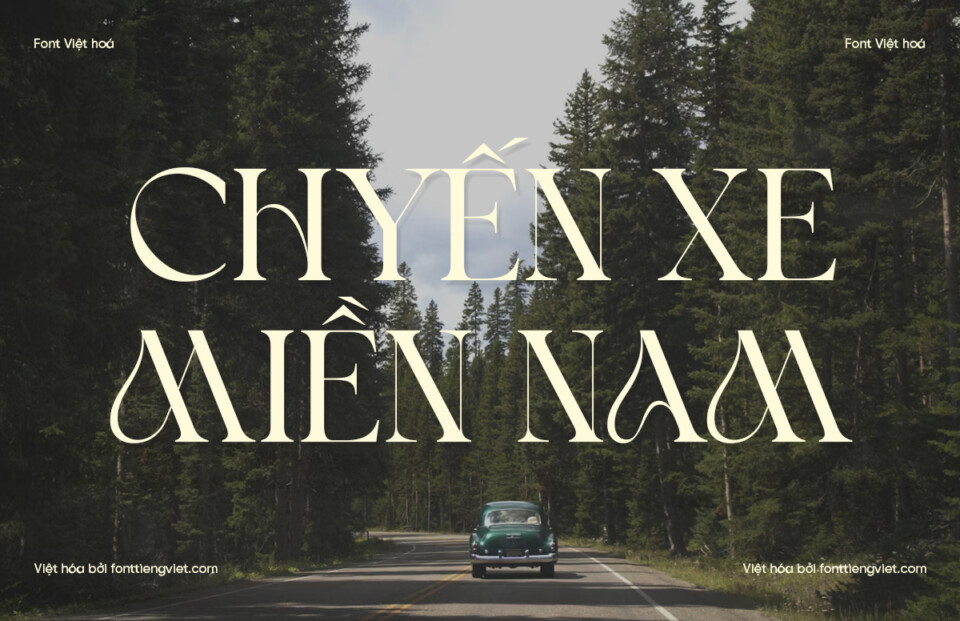
Tải Font Việt hóa 1FTV VIP Lamoric Rowen – Đỉnh Cao Thiết Kế Sang Trọng
Giới thiệu về Font Việt hóa 1FTV VIP Lamoric Rowen
Trong thế giới đồ họa hiện đại, việc lựa chọn Font Miễn Phí chất lượng đóng vai trò quyết định đến thẩm mỹ của sản phẩm. Font Việt hóa 1FTV VIP Lamoric Rowen là một bộ font chữ mang phong cách serif cổ điển kết hợp hơi thở đương đại, tạo nên vẻ đẹp thanh lịch và đầy quyền quý. Được đội ngũ 1FTV tinh chỉnh kỹ lưỡng, bộ font này hỗ trợ đầy đủ tiếng Việt, giúp các nhà thiết kế tại Việt Nam dễ dàng ứng dụng vào nhiều loại hình dự án khác nhau từ học tập đến làm việc chuyên nghiệp.
Đặc điểm nổi bật của bộ font VIP
Bộ Font Việt hóa 1FTV VIP Lamoric Rowen sở hữu những đường nét mảnh mai nhưng vô cùng sắc sảo. Các nét thanh và nét đậm được phân bổ hài hòa, tạo cảm giác dễ nhìn và sang trọng. Đặc biệt, các ký tự thay thế (alternates) và chữ ghép (ligatures) đi kèm giúp người dùng tự do sáng tạo những logo, tiêu đề sách hay thiệp mời độc bản. Đây chính là lựa chọn hàng đầu cho những ai yêu thích sự tinh tế trong từng con chữ.
Ứng dụng Font Việt hóa 1FTV VIP Lamoric Rowen trong thực tế
Với phong cách quý tộc, Font Việt hóa 1FTV VIP Lamoric Rowen thường được ưu tiên sử dụng trong thiết kế nhận diện thương hiệu thời trang, mỹ phẩm và các ấn phẩm nghệ thuật. Trong môi trường giáo dục, thầy cô và học sinh có thể dùng font chữ này để trang trí bìa tiểu luận hoặc bài thuyết trình để tăng tính thẩm mỹ và chuyên nghiệp. Sự đa dạng trong định dạng giúp font hoạt động mượt mà trên nhiều phần mềm như Photoshop, Illustrator hay Canva.